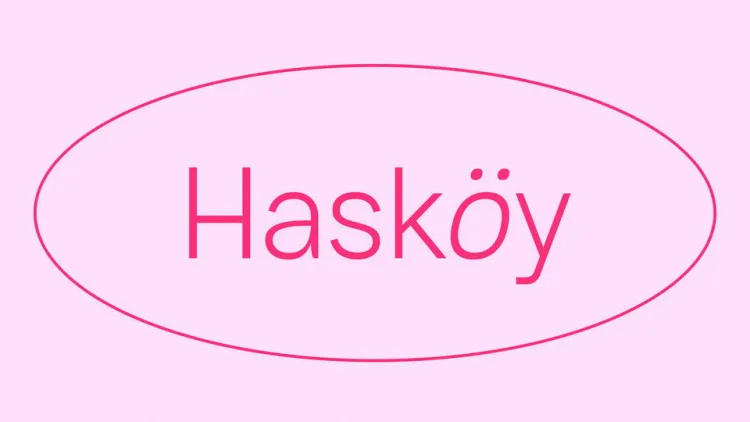
Hasköy Font Family – Download Grátis
A Hasköy Font Family é uma família de fóntes sans-serif que não morre nunca, destinada a ser usada constantemente em diversas ocasiões ou trabalhos de exibição. Desenhadas com poderosas características do OpenType, esta fonte inclui suporte para linguagens latinas-estendidas e alternativas estilizadas além das fracções, as figuras tabulares e os símbolos de setas. Suas variações proporcionam tanto uma variedade quanto o controle necessário ao criar design gráfico atraentes, legíveis e eficazes. Seja você um designer web, um editor gráfico ou até mesmo um criador de conteúdos em redes sociais, Hasköy oferece a oportunidade de agregar valor a seus trabalhos com uma fonte que não apenas se adapta bem ao seu formato atual, mas também o acompanha para sempre.